16 migliori font di tracciamento del 2023 (gratuiti e premium)
Pubblicato: 2023-10-01Ti sei mai chiesto come far risaltare davvero i tuoi progetti di design? Sei un graphic designer alla ricerca del font perfetto per valorizzare il tuo lavoro? Non guardare oltre!
In questo post del blog, ci immergeremo in profondità nel mondo dei caratteri di tracciamento, un potente strumento che può portare i tuoi progetti a un livello superiore.
Quando si tratta di tipografia, la scelta del carattere giusto è fondamentale. I caratteri hanno la capacità di trasmettere emozioni, dare il tono e persino influenzare il modo in cui le persone percepiscono il tuo messaggio.
Tuttavia, con gli innumerevoli caratteri disponibili, può essere difficile trovare quello che si adatta alla tua visione. È qui che entrano in gioco i caratteri di tracciamento.
I caratteri tracciati ti consentono di creare design unici e accattivanti sovrapponendo contorni o ricalcando lettere esistenti. Questa tecnica aggiunge un tocco personalizzato al tuo lavoro, rendendolo davvero unico nel suo genere.
Inoltre, i caratteri di tracciamento possono essere utilizzati in una varietà di progetti, da loghi e intestazioni di siti Web a packaging e grafica per social media.
In questo articolo ti illustreremo i vantaggi dell'utilizzo dei caratteri di tracciamento e ti forniremo alcuni suggerimenti su come integrarli perfettamente nei tuoi progetti. Iniziamo!
I migliori font di tracciamento Premium
Desideri portare la progettazione dei tuoi progetti al livello successivo? Non cercare oltre la nostra selezione selezionata dei migliori caratteri di tracciamento premium.
Questi caratteri aggiungeranno sicuramente un tocco di professionalità e creatività al tuo lavoro. Non perdere l'occasione di scoprire il carattere perfetto per il tuo prossimo progetto: continua a leggere per esplorare le nostre scelte migliori!
Traccia
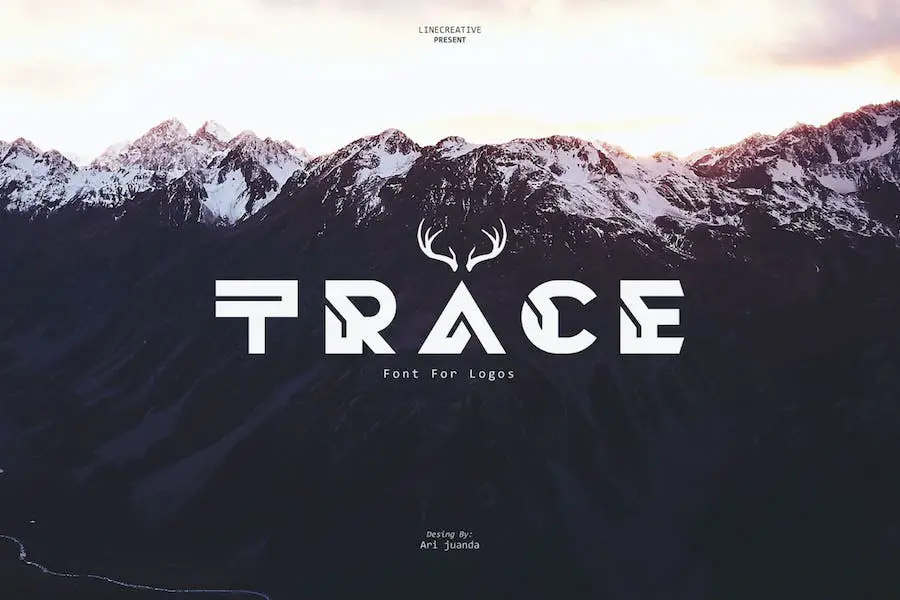
Trace è un carattere San Serif pulito e ordinato, perfetto per i grafici che desiderano migliorare il design dei loro progetti.
Con caratteri sia maiuscoli che minuscoli, questo carattere di Google Tracing offre versatilità e creatività per qualsiasi testo. Include anche numeri e segni di punteggiatura, rendendolo un pacchetto completo per tutte le tue esigenze di progettazione.
Inoltre, supporta più lingue, assicurandoti di poterlo utilizzare per vari progetti senza alcuna limitazione. Trace è il carattere definitivo per i designer che vogliono portare i loro progetti a un livello superiore.
Manuale TF
TF Handschrift è un carattere che dà vita ai tuoi progetti con il suo testo/sensazione di scrittura autentica. Derivato dalla vera scrittura a mano di una penna a sfera, questo font Adobe Tracing è tracciato e regolato digitalmente per un utilizzo ottimale.
È perfetto per aggiungere un tocco personale ai tuoi progetti e creare un'esperienza coinvolgente.
Con i suoi caratteri multilingue, TF Handschrift garantisce che il tuo testo venga compreso e apprezzato da un pubblico globale. Migliora il tuo gioco di design con questo carattere versatile e unico.
Angelline
Angelline è un carattere calligrafico in rame che fonde perfettamente gli stili di scrittura in rame e contemporanei, dando vita a un design sofisticato e aggraziato.
Il suo aspetto artigianale, con una linea di base giocosa, aggiunge un elemento di fascino ed eleganza a qualsiasi progetto. Con un'ampia gamma di 348 glifi dal design accattivante, inclusi contesti, legature e caratteri alternativi, Angelline offre infinite possibilità creative.
Sia che lo utilizzi in un programma OpenType Savvy o che selezioni manualmente i caratteri dalla tavolozza dei glifi, questo carattere di tracciamento per Word farà sicuramente risaltare i tuoi progetti.
TF-Kugelschreiber
TF-Kugelschreiber è un carattere che porta il fascino del testo scritto a mano nei tuoi progetti di design. Creato dal tracciato preciso della nostra vera calligrafia con penna a sfera, questo carattere conferisce al tuo testo un tocco autentico e personale.
Che tu stia lavorando su inviti, loghi o qualsiasi progetto che richieda un aspetto organico, TF-Kugelschreiber è la scelta perfetta.
Inoltre, questo font Tracing per Canva include caratteri multilingue, rendendolo versatile per varie esigenze linguistiche. Dì addio ai caratteri generici e lascia che TF-Kugelschreiber aggiunga un'atmosfera unica e genuina ai tuoi progetti.
Amore Quake
Love Quake è un font delizioso che offre caratteri tracciati a mano al 100%. Trae ispirazione dal movimento delle arti e dei mestieri e vanta un affascinante gusto acquerello.
Con il suo allegro stile a pennellata, questo carattere è perfetto per aggiungere un tocco di creatività a qualsiasi progetto. Inoltre, viene fornito con barre aggiuntive e un file vettoriale, consentendo una versatilità ancora maggiore.
Sia che tu stia cercando di combinare lettere maiuscole e minuscole, aggiungere turbinii e barre o esplorare caratteri e legature alternative, Liebe Quake ti copre. Questo Tracing Fonts per Cricut è altamente raccomandato per tutte le tue esigenze di visualizzazione.